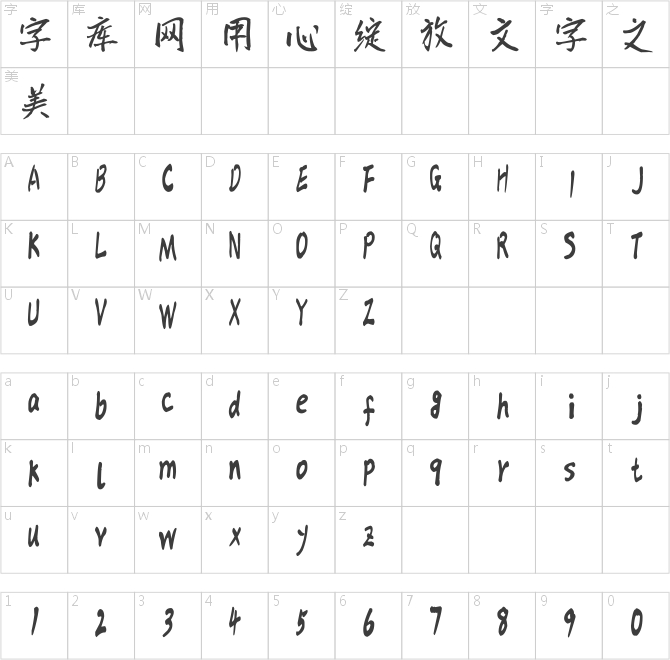
漢標(biāo)儒雅楷書 詳情頁
字體名稱: 漢標(biāo)儒雅楷書
漢標(biāo)儒雅楷書
漢標(biāo)儒雅楷書介紹
漢標(biāo)儒雅楷書字體儒雅楷書字庫是一款讓人賞心悅目、百看不厭的中文字體,適合各類廣告和產(chǎn)品包裝設(shè)計(jì)應(yīng)用,字體大小3.78MB,格式為ttf字體,上傳用戶是漢標(biāo)文創(chuàng),作者/版權(quán)方為漢標(biāo)字庫